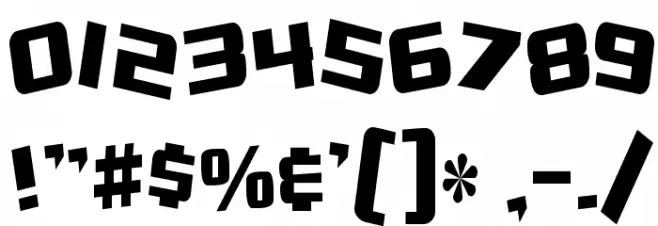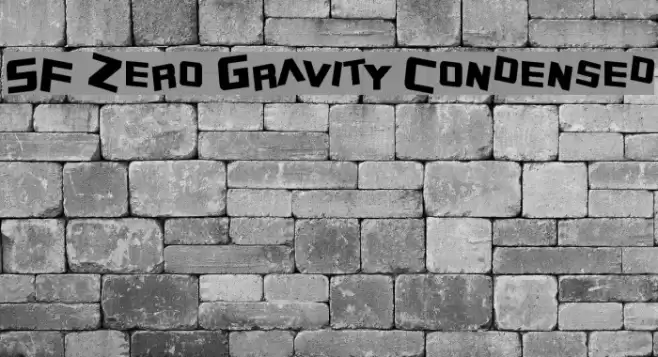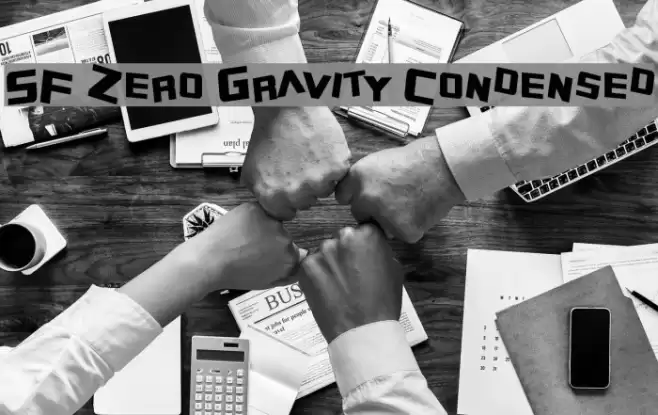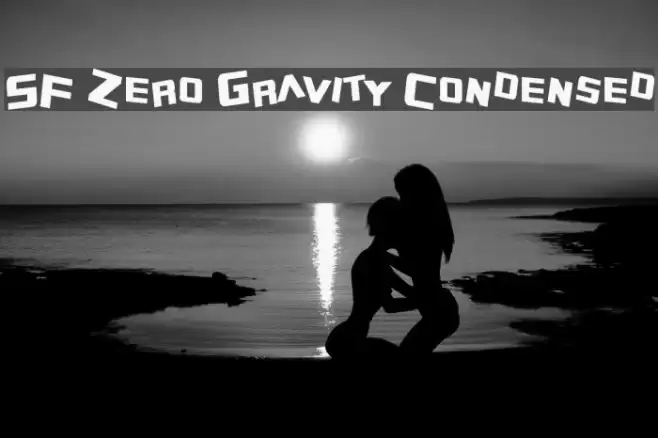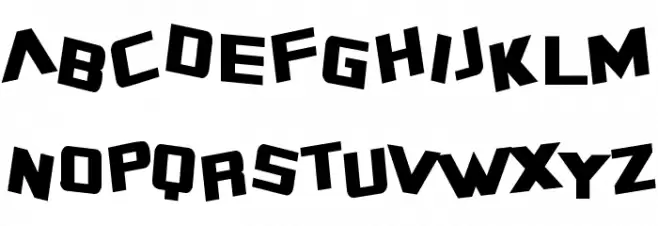
SF Zero Gravity Condensed Font
✎ Wavy
| Proiecte propuse | Ideal for sci-fi themed projects, video game titles, posters, and branding that requires a modern and energetic look. |